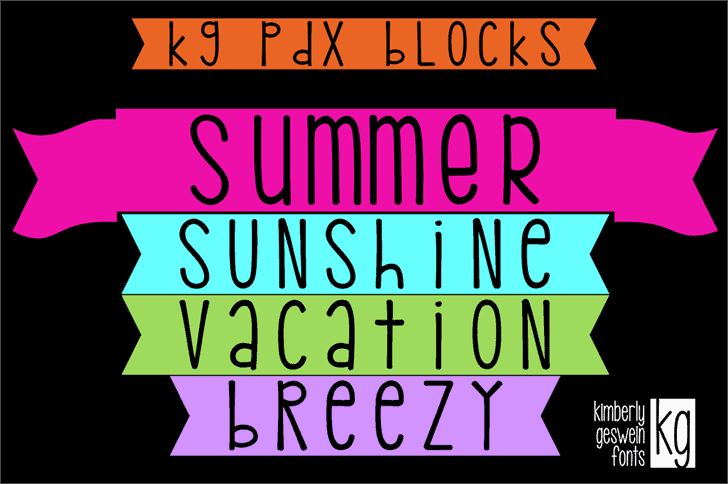
A fonte KG PDX Blocks é uma escolha perfeita para quem busca estilos modernos e icônicos para seus projetos gráficos. Lançada em 2015 pela designer Kimberly Geswein, esta fonte sans-serif apresenta um design minimalista que traz à tona elementos geométricos e desenhos cubistas, criando um visual contemporâneo e vibrante. Com uma série de blocos arredondados e formas geométricas esparsas, a KG PDX Blocks oferece uma variedade rica para adaptar ao seu estilo único. A fonte é perfeita para headlines em banners, títulos em páginas web ou qualquer projeto que exija um toque moderno e criativo. O conjunto de guia incluído no PDF é bastante útil e permite aos usuários explorarem as infinitas possibilidades desse design único. Essa fonte não apenas adicionará uma nova dimensão à sua composição visual, mas também permitirá que você transmita seu próprio estilo e mensagem de maneira ainda mais clara e impactante. Visite KimberlyGeswein.com para obter informações detalhadas sobre a licenciagem da fonte, caso seja necessário.